设计过程
整体设计思路是采用了视觉暂留的原理。
视觉暂留
人眼在观察物体时,光信号传入大脑神经需要时间,光的作用结束后,视觉形象并不立即消失。前一帧的图像在视网膜上短暂停留时,后一帧图像已经显示出来。当这种连续帧图像快速切换时,大脑会将它们感知为一个流畅的运动画面,实现动画效果。
简单点说就是通过条纹遮挡,使得单一的一张图能呈现出动画的效果。
我这里制作的是三帧动画,具体计算过程就不讲了,挺简单的。只需要依次用栅格条纹将这三帧的图像遮挡部分给减去,然后合并在一起,就可以制作出栅格动画需要的图像了。
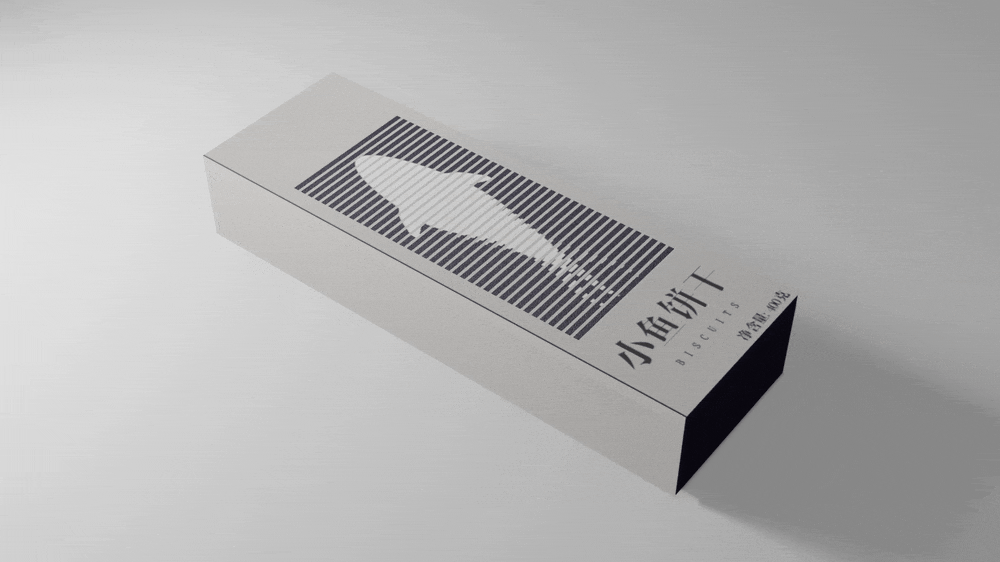
设计理念
这个主要是侧重于展示创意,目前呈现的外包装视觉呈现相对简洁,侧重于核心动画效果的实现:
消费者在抽出包装内盒时,透过覆盖的栅格条纹,就能观察到小鱼游动的动画效果。
在此设计中,盒子主体我选用了浅灰色调,配合黑色醒目字体标示产品名称“小鱼饼干”和关键信息(BISCUITS、净含量400克),意在不过度干扰动态区的视觉效果。明确标识“小鱼饼干”的中英文名称也确保了产品的辨识度。
总的来讲,此设计的核心价值在于其创意实现和互动性。这种带有趣味性和科技感的设计非常适合追求新鲜感和独特体验的年轻消费群体,也非常契合零食(尤其儿童或年轻向零食)、小型电子消费品、创意玩具礼品等品类。对于追求极度简约低调或稳重风格的产品品类,其适用性则需具体评估。
像之前月饼盒还没被批评为“过度包装”的时候,这么设计应该挺适合用来送礼。但现在就不好说了,只能说是有意思,但实用价值有待商榷。